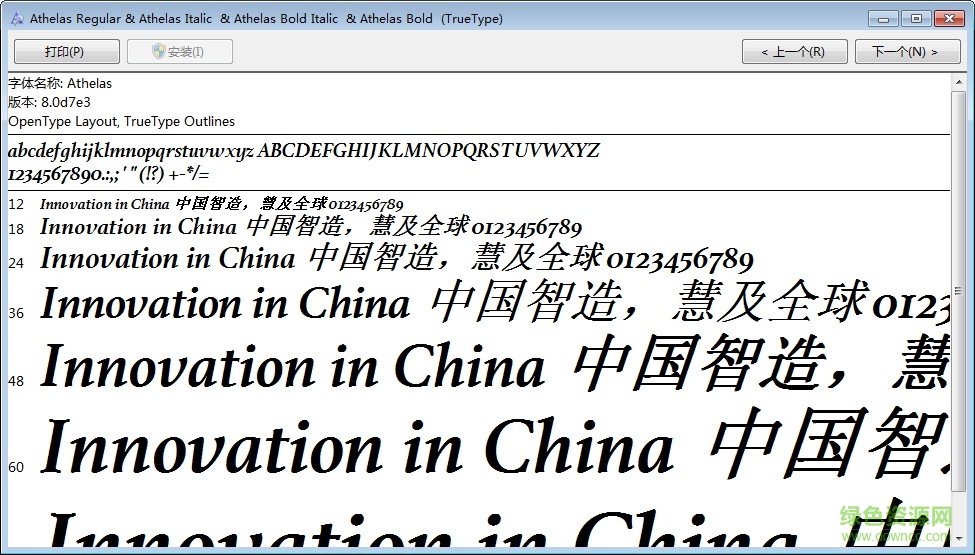
athelas bold italic是一款免費的英文字體,字體粗黑堅實,氣勢雄健,莊重大方,表現(xiàn)力強,喜歡的朋友歡迎在綠色資源網(wǎng)下載!
意大利體起源于手寫體,16世紀初在意大利威尼斯就已經(jīng)出現(xiàn)為節(jié)省版面的斜體。由于起源于手寫體,字形向右傾斜是其最大特征。最初是與正文完全不同的獨立字體出現(xiàn)的,現(xiàn)在電腦字體中已經(jīng)作為在襯線體字體的一部分收入,在正體排版中需要強調(diào)、區(qū)別的時候使用。